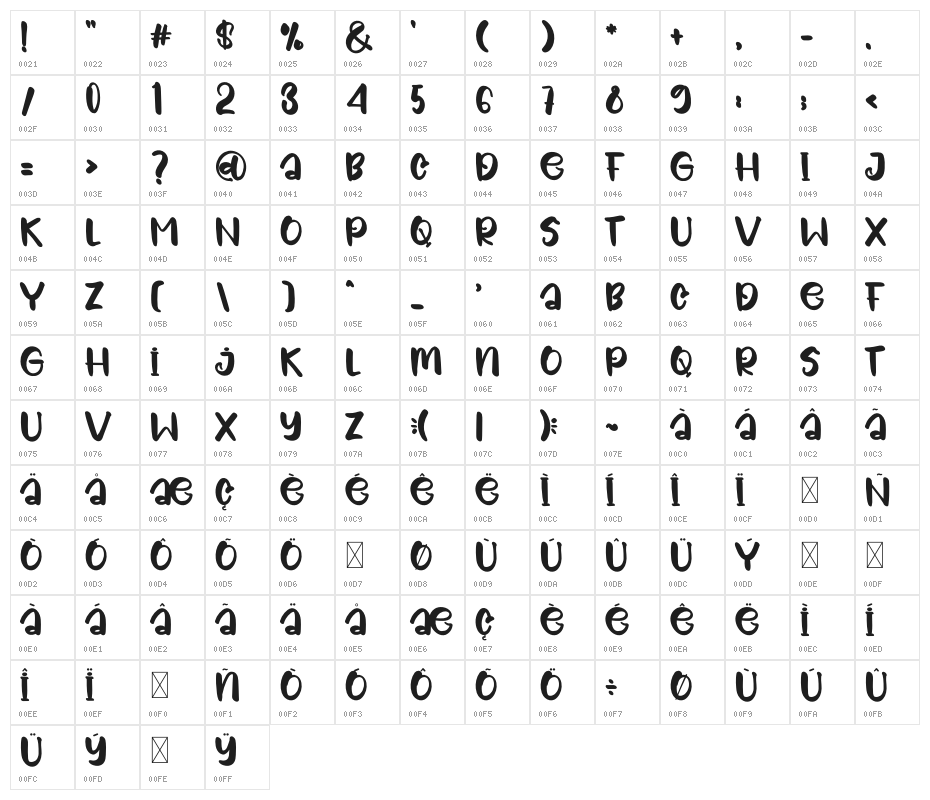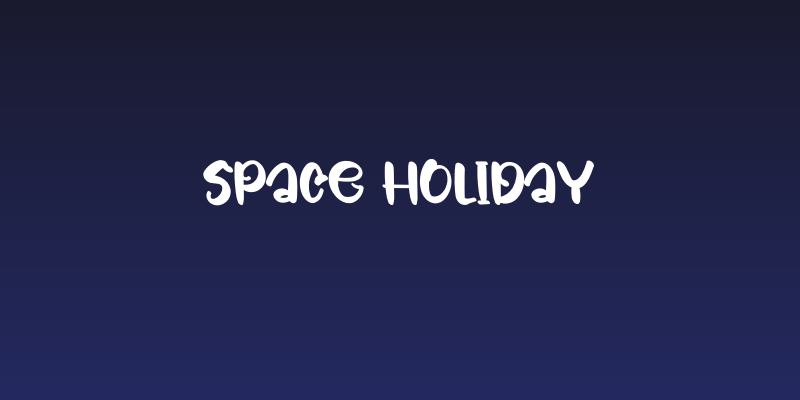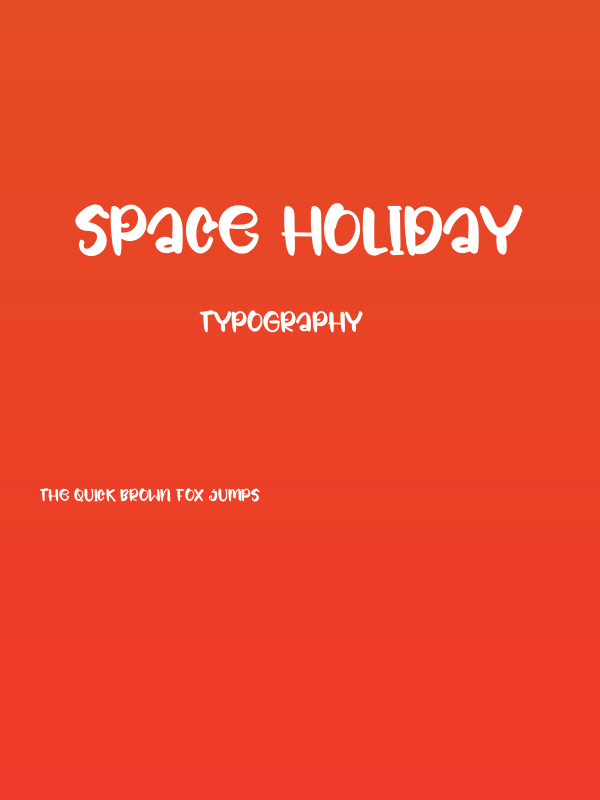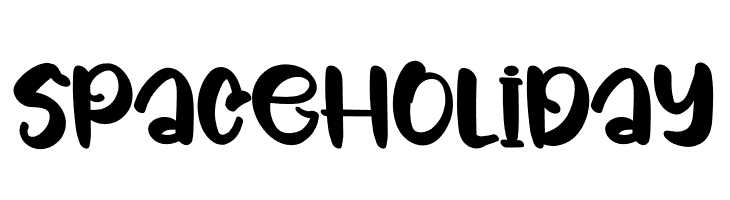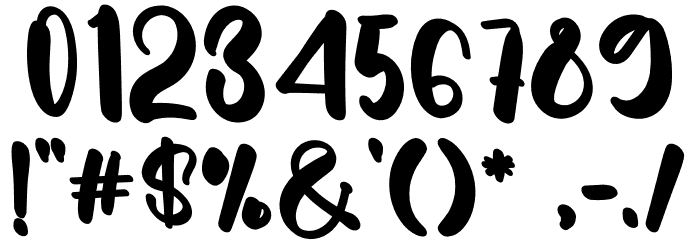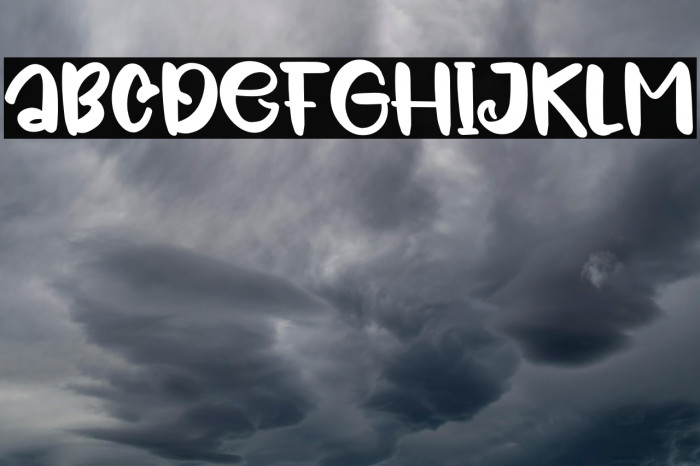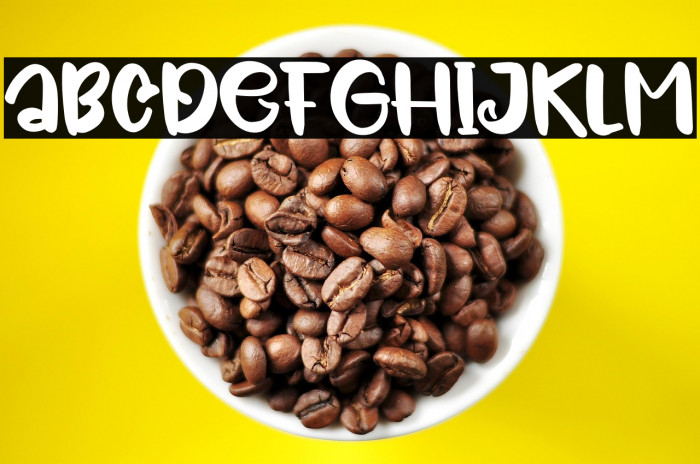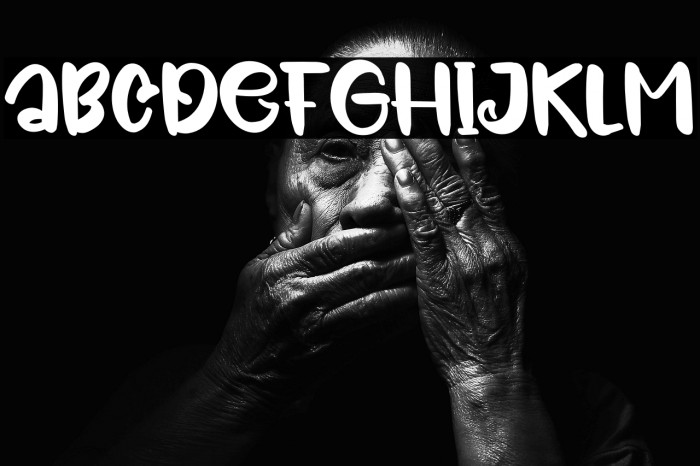
Space Holiday Font
Fonts by Inermedia Studio
| श्रेणियाँ | Cartoon |
| समग्र शैली | Decorative |
| उपयोग का मामला | Headlines, Logos, Invitations |
| सुझाए गए प्रोजेक्ट | Ideal for holiday-themed designs, children's books, party invitations, and playful branding projects. |